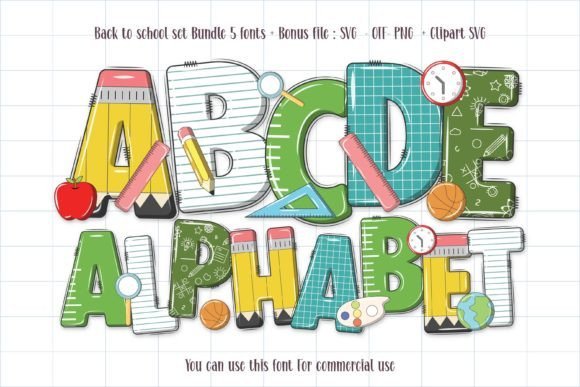
Back to School Set Font
Back to School Set Font – مجموعة الخطوط المثالية للعودة إلى المدرسة!
اجعل تصاميمك أكثر إبداعًا ومرحًا مع Back to School Set Font، المجموعة المثالية التي تضيف لمسة تعليمية وودودة إلى مشاريعك. سواء كنت تصمم ملصقات مدرسية، أو دفاتر ملاحظات، أو منشورات على وسائل التواصل الاجتماعي، أو حتى مواد تعليمية، فهذه الخطوط ستساعدك على إبراز أفكارك بأسلوب مميز وممتع.
✅ تصميم جذاب وسهل القراءة يناسب الأطفال والكبار